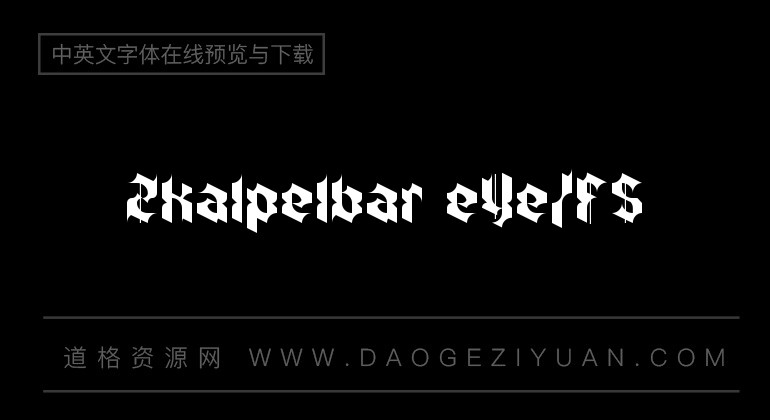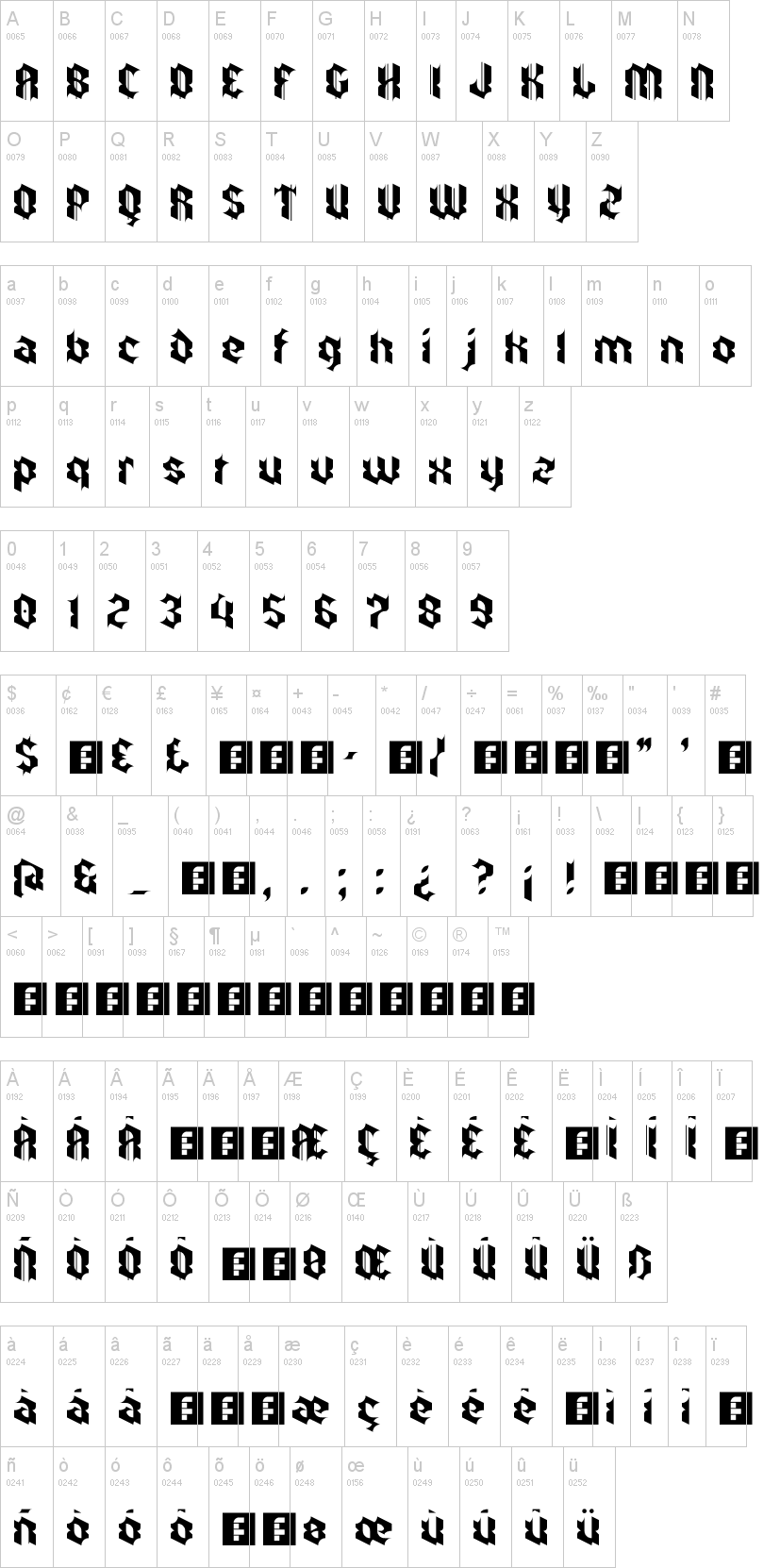
Zkalpelbar eYe/FS
Zkalpelbar eYe/FS是一款细腻而精美的字体,它由著名的设计师Zkalpelbar创作。这款字体具有非常优秀的设计,其细节和精致的外观让它成为一款非常受欢迎的字体。它具有清晰的文字和精致的外观,可以用于各种不同的场景,是一款非常适合用于商业用途的字体。
Zkalpelbar eYe/FS是一款非常不错的手写艺术字体,具有很好的视觉感,适合于文化类的宣传设计、商业类品牌的广告和产品包装设计以及个性化文字排版等较多场景。
Zkalpelbar eYe/FS字符映射图